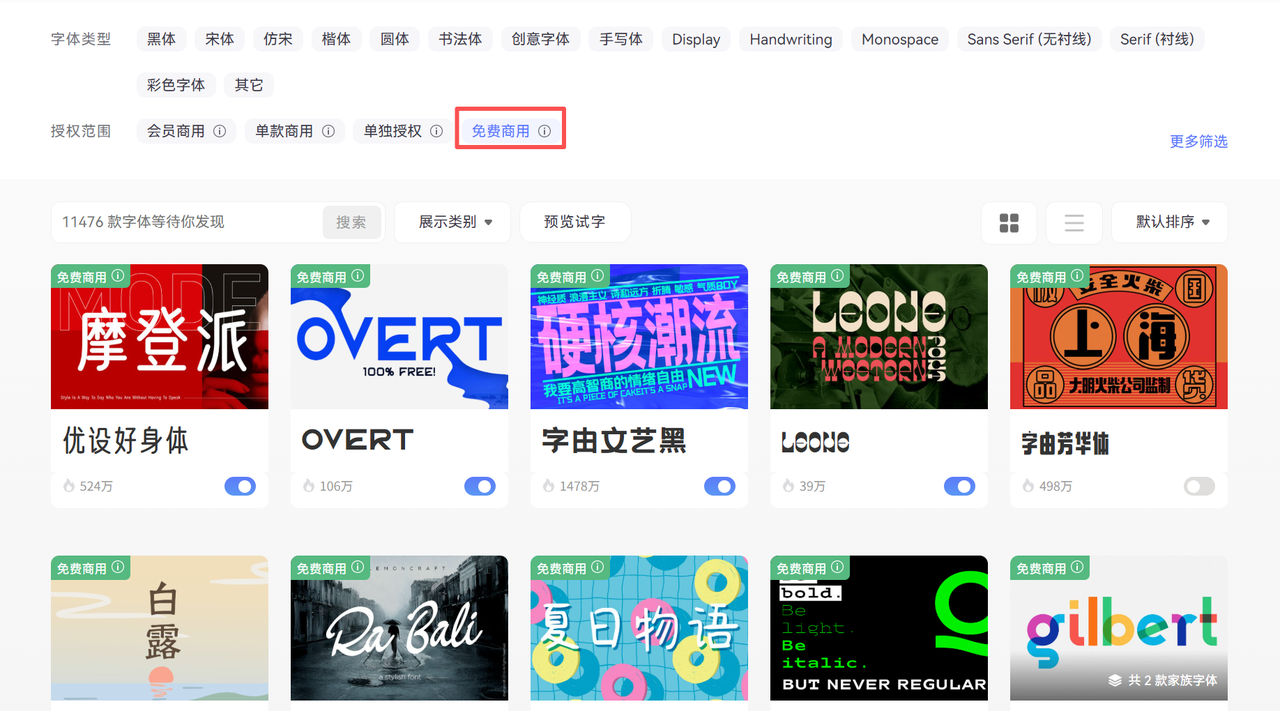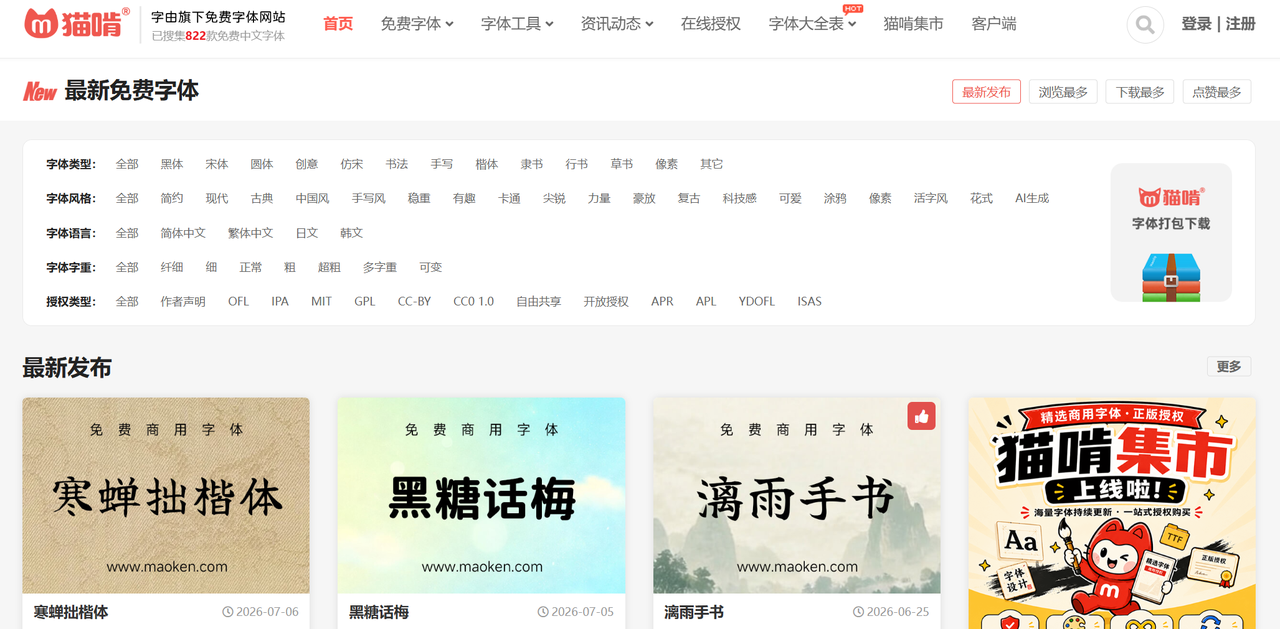
免费商用空心字体下载网站推荐:6个平台实测分享
去年我接手一个品牌设计项目时,客户希望logo用空心字体来呈现轻盈感和现代感。我当时在网上随便下载了一款看起来不错的空心字体,结果使用后才发现是有版权限制的,差点给公司带来法律风险。后面我自己找到了一些免费空心字体的下载网站,今天就分享给大家。
我现在主要使用字由这个平台来管理和下载字体。字由不仅是一个字体下载平台,更是一个实用的字体管理工具,它可以直接和Photoshop、Illustrator等设计软件联动,使用起来非常方便。
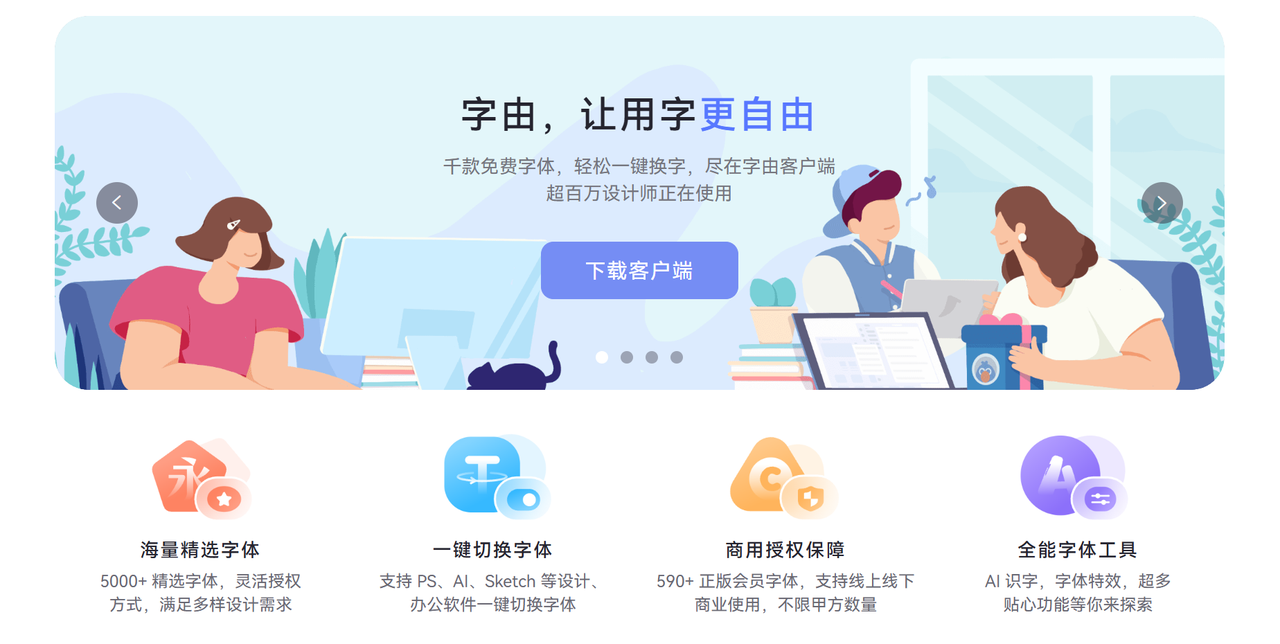
在字由平台上,我发现了几款质量不错的免费商用空心字体,这里分享给大家:
- 站酷酷黑
站酷的字体在设计圈口碑一直很好。虽然站酷酷黑本身不是空心字体,但它的字形结构很适合改造成空心效果。我在实际项目中经常用它的描边功能做出空心效果,线条粗细均匀,视觉效果很稳定。
- 优设标题黑
这款字体的笔画比较粗壮,转换成空心字体后识别度依然很高。我用它做过几次海报标题,客户反馈都说看起来很有力量感。字由平台上可以直接下载,授权协议写得也很清楚。
- 阿里巴巴普惠体
阿里出品的这款字体家族很全,从细体到粗体都有。我个人比较喜欢用它的Medium和Bold版本做空心处理,出来的效果比较现代,适合科技类和互联网类的设计项目。
- 思源黑体
这是Adobe和Google联合开发的开源字体,字重选择很多。我通常会选择较粗的字重版本来制作空心字体,因为笔画太细的话做成空心后容易看不清。思源黑体的优点是字库完整,基本不会遇到缺字的情况。
在字由官网的免费商用字体页面上,你可以通过筛选功能找到更多适合的字体。我的使用习惯是先在这个页面上预览效果,觉得合适了再通过字由客户端下载安装。
猫啃网
猫啃网是我发现的一个专门收录免费商用字体的网站。这个平台最大的优点是把每款字体的授权信息整理得特别清楚,我每次下载前都会看一眼授权说明,心里踏实。
网站上的字体分类做得很细致,可以按照字体风格、语言、授权类型来筛选。我印象最深的是它会标注每款字体的更新时间,这样能确保我下载到的是最新版本。虽然猫啃网上直接提供的空心字体不多,但很多黑体字都适合转换成空心效果。
100font
100font这个网站的界面很简洁,收录的都是精选的免费字体。我喜欢它的一点是每款字体都配有实际应用案例,能直观看到字体用在设计中是什么效果。
这个平台更新频率不算高,但收录的字体质量都比较稳定。我曾经在这里找到过几款日文字体,转换成空心后用在一些需要异国风格的设计项目中,效果出乎意料地好。
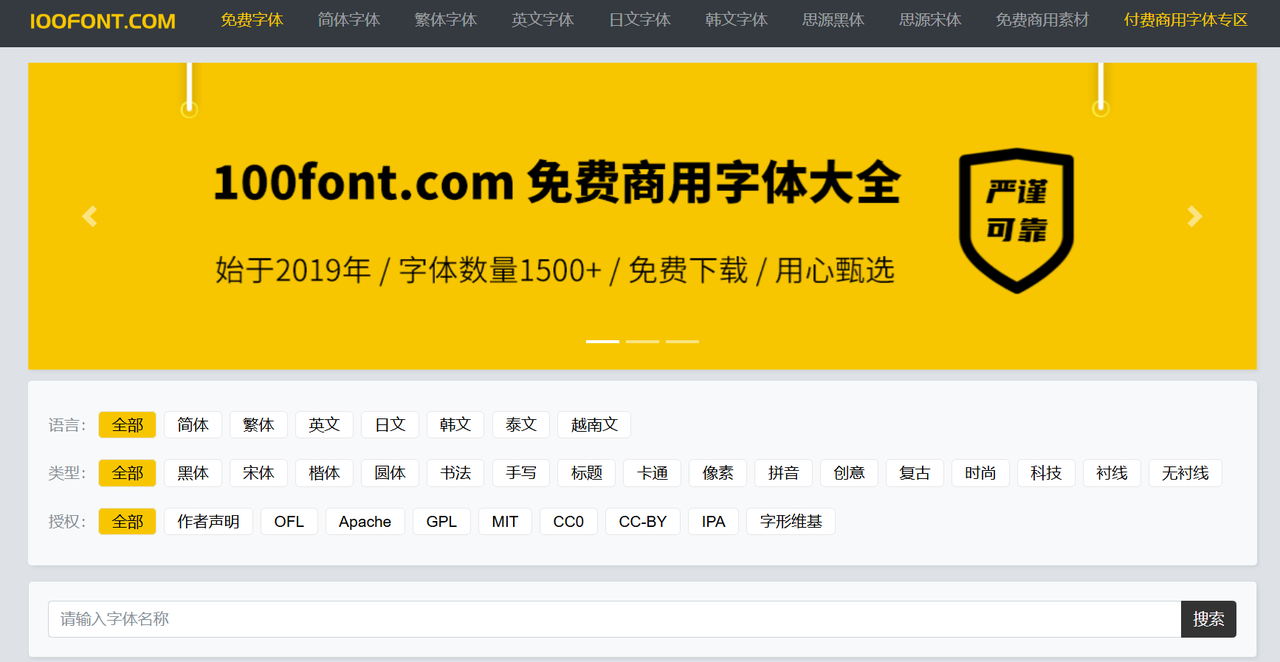
字体天下
字体天下是一个老牌字体网站,资源很丰富。不过需要注意的是,这个平台上既有免费字体也有商业字体,下载前一定要仔细看授权说明。
我通常会在搜索时加上"免费商用"这个关键词来筛选。这个网站的优势是字体数量多,有时候能找到一些比较冷门但很有特色的字体。我做复古风格设计时,就经常在这里淘字体。
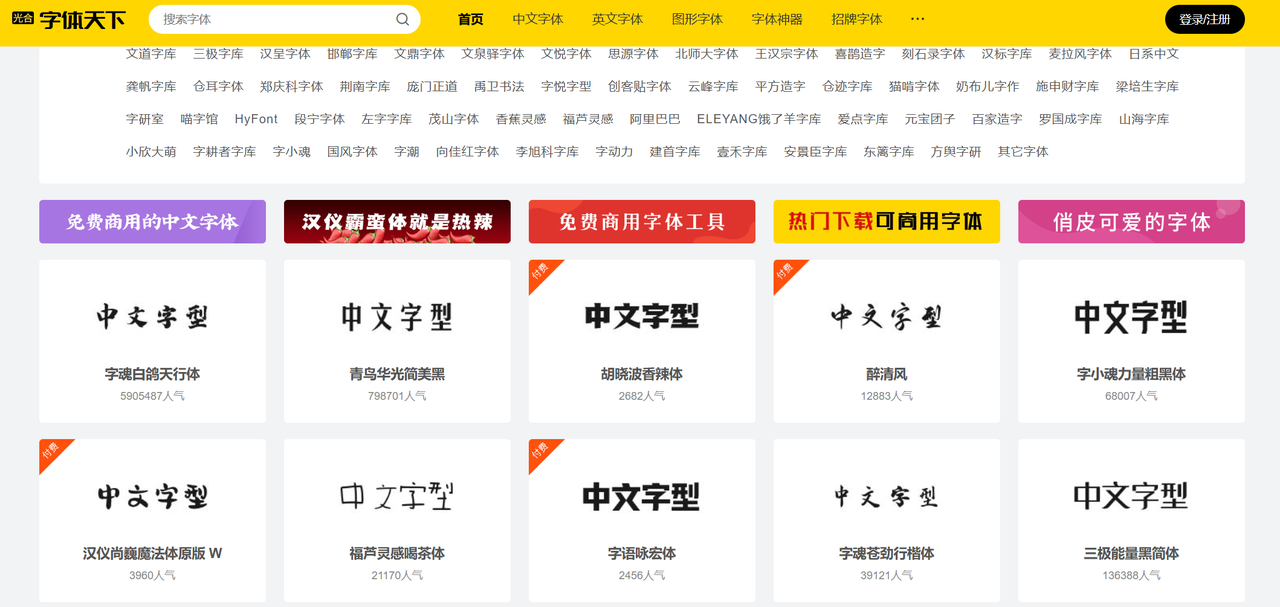
求字体网
求字体网有一个很实用的功能——字体识别。有时候我在网上看到好看的字体但不知道名字,就会用这个平台的识别功能来查找。
网站上也提供免费字体下载,不过相比其他平台,这里更多是作为一个辅助工具来使用。我的工作流程通常是:先在求字体网识别出字体名称,然后再到其他平台去找免费的替代方案。
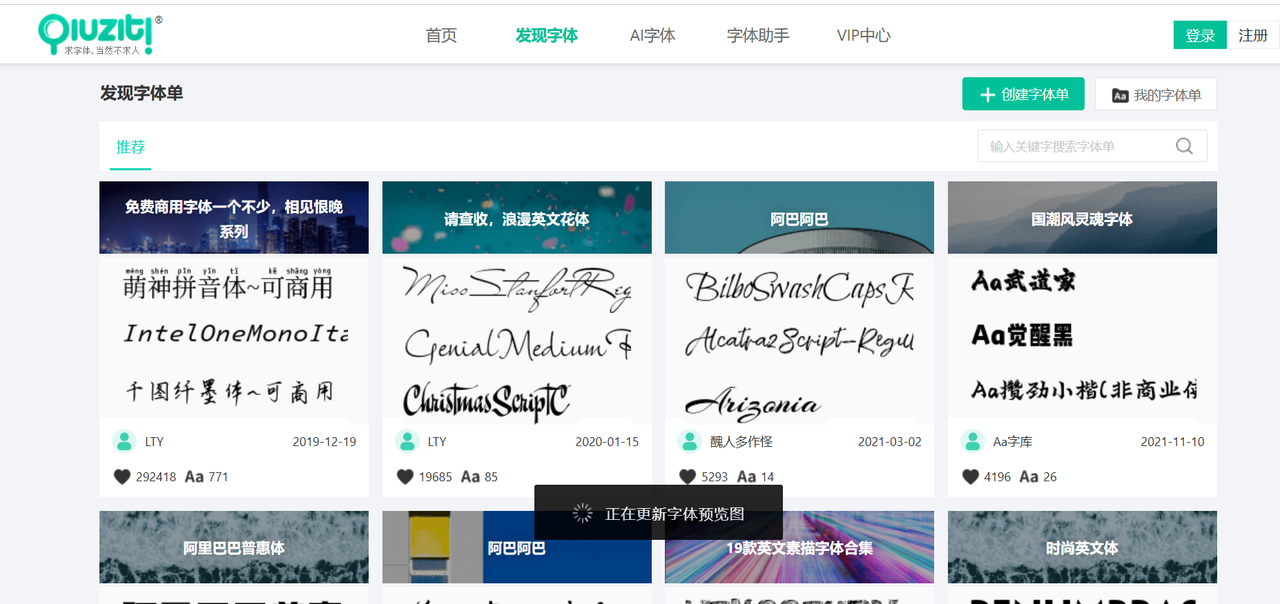
自由字体
自由字体这个平台是一个开源字体的聚合站,收录的基本都是可以免费商用的字体。我欣赏它的地方在于每款字体都会标注具体的开源协议类型,比如SIL Open Font License或Apache License。
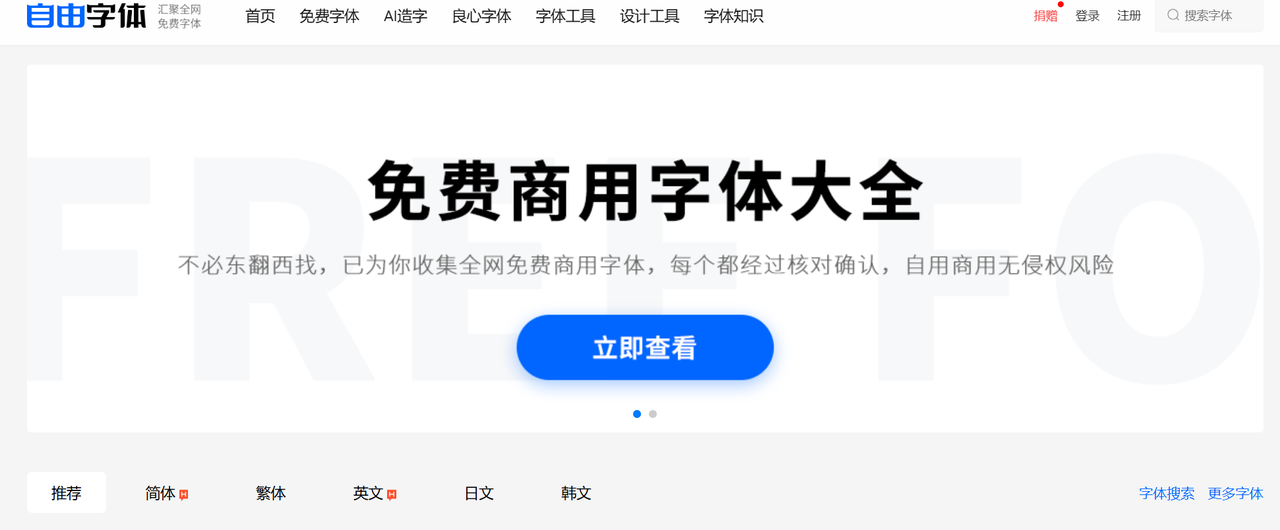
找到合适的免费商用空心字体确实需要花些时间,但这个过程是值得的。通过使用正规渠道的免费字体,我不仅避免了版权风险,还为公司节省了不少字体授权成本。
现在我的工作流程是:需要空心字体时,先到字由平台上浏览免费商用字体,找到合适的字体后下载安装,然后在设计软件中自己制作空心效果。如果字由上找不到满意的,我会再到猫啃网、100font这些平台上继续寻找。